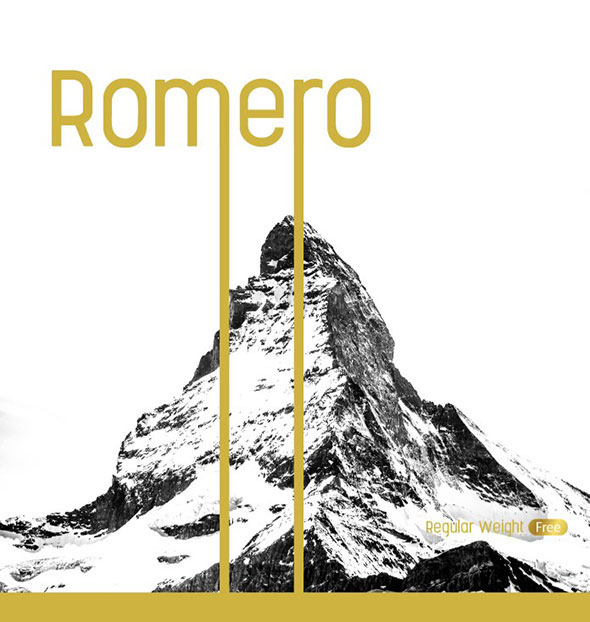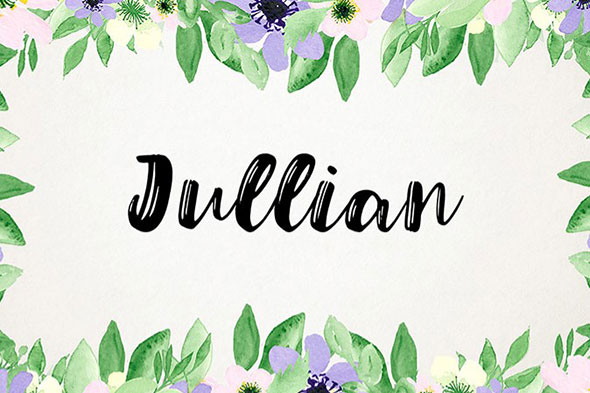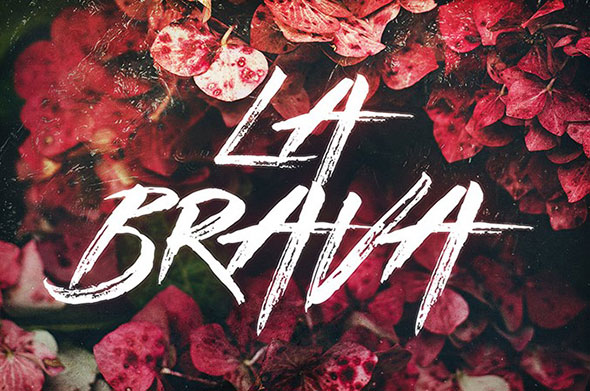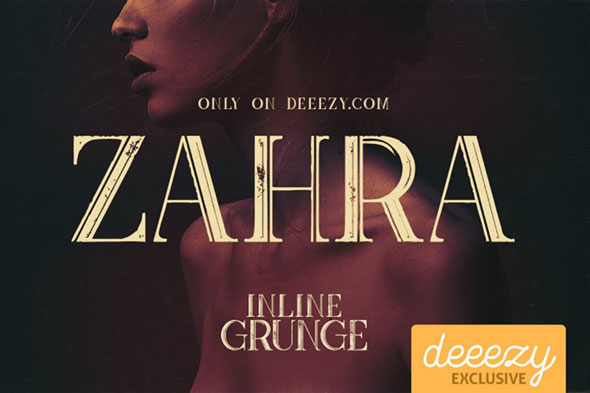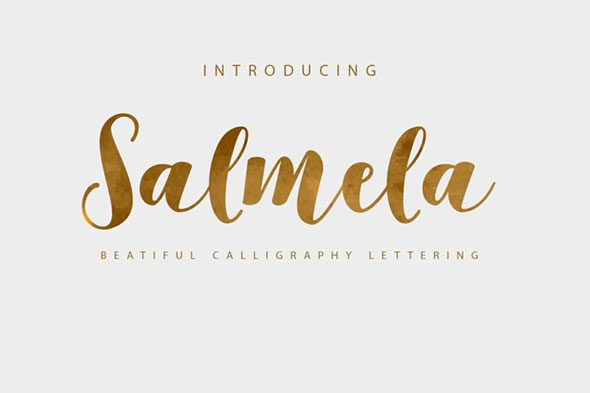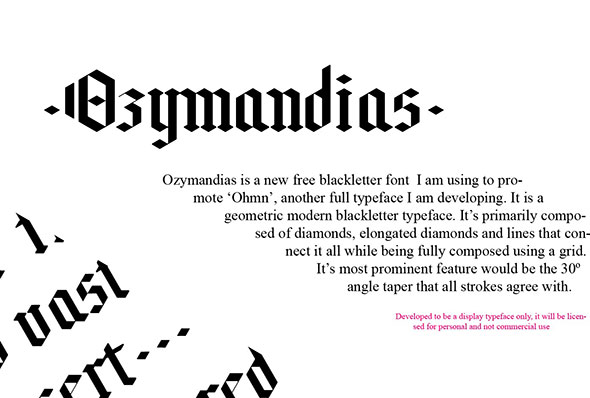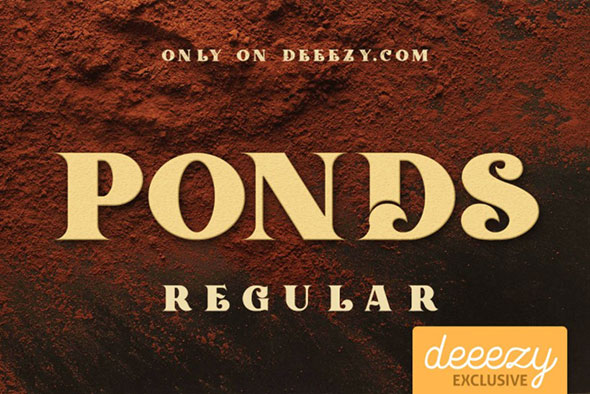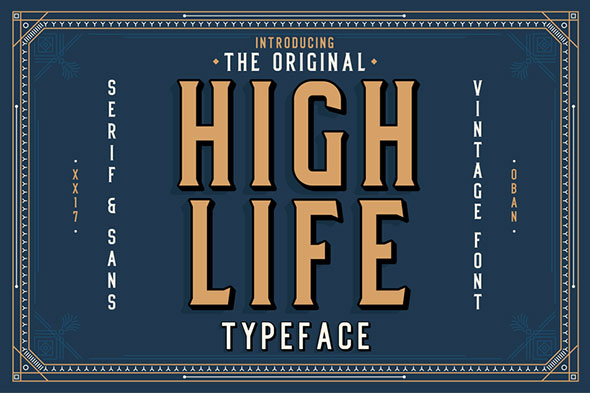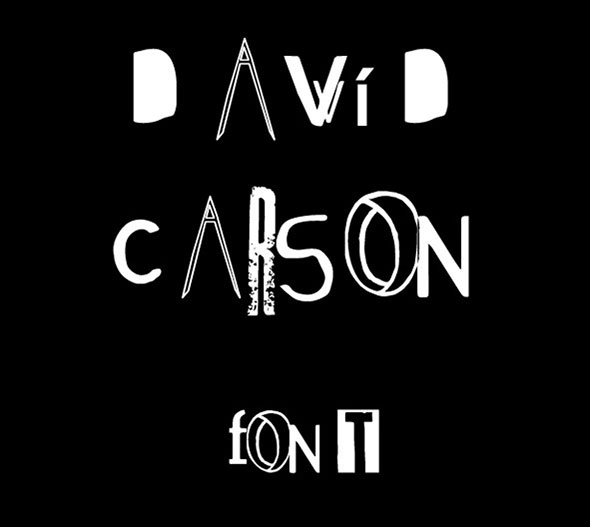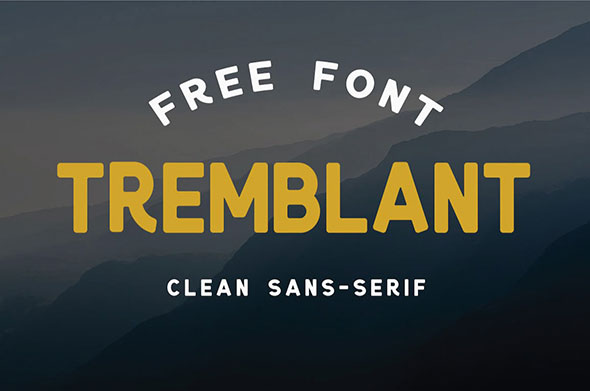
Декоративные шрифты для вашего дизайна
Пополняем коллекцию шрифтов. Сегодня мы собрали свежие и бесплатные примеры декоративных шрифтов. Оно подойдут для больших надписей, чтобы подчеркнуть то или иное настроение ваших дизайн-проектов. Используйте их для заголовков, оформления лозунгов или поздравлений на открытках.
Romero Regular
Ozymandias
Ponds
High Life
David Carson
TREMBLANT
HOT ROD
Freeday Script & Sans Font
Bahagia
Bant Achillers
Julian
La Brava
Zahra Inline Grunge Font
Aila
Salmela